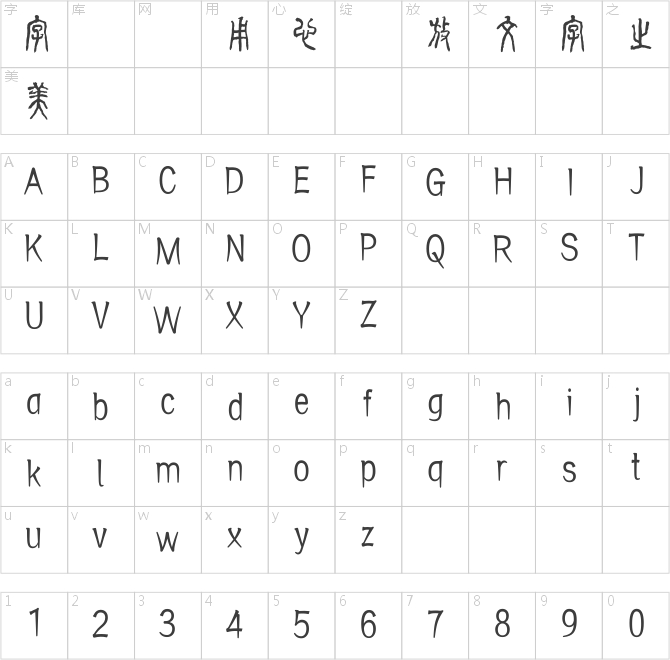
方正字迹-顾建平酷篆体
方正字迹--顾建平酷篆体,由上海交大文化创意奖、新加坡杰出贡献奖、文化艺术奖得主,文字学家、书法家顾建平所创。如菩萨亦男亦女造型,现代中性跨界打扮,酷篆运用古老东方中庸智慧与现代审美中性风尚,突破传统小篆婉约柔美局限,刚柔相济、拙秀并用,独创雅俗共赏、男女皆宜的炫酷篆书??嶙乇鹗屎嫌笆?、游戏、广告、包装等用字。